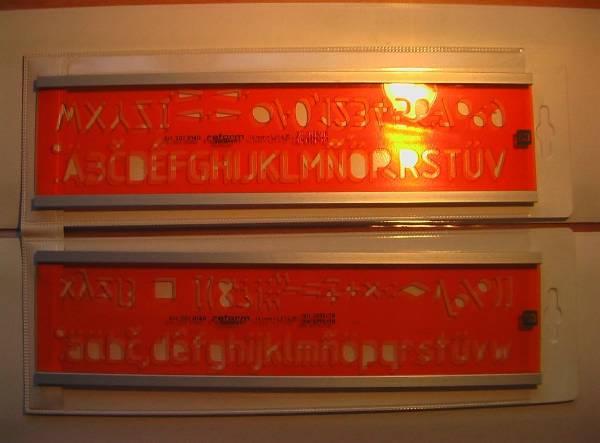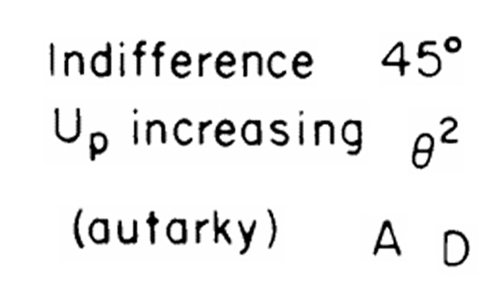
serifenlose Grafik-Schriftart aus einem wissenschaftlichem Paper der 70er Jahre gesucht
wie der Thementitel aussagt suche ich folgende Schriftart:
Das sieht aus wie eine der vielen typische (aus der Futura abgeleitete?) nordamerikanische Fibelschriften, also Schulbuchschriften. Diese Schriften sind nach dem zweiten Weltkrieg gelegentlich/selten auch in deutschen Lernmitteln aufgetauscht aber dann schnell wieder verschwunden. Einige Hochschuldruckereien haben in den guten alten Bleisatzzeiten bis in die 1980er solche Schriften noch verwendet. Ich habe da noch den einen oder anderen Schein rumliegen. Da gibt es einige freie Versionen, aber die sind alle etwas unpassend:
Deine Vorlage ist leicht condensed und ich finde gerade keine solche Schrift, habe diese aber schon mehrfach gesehen, nicht nur als Bleisatz. Leider ist mein Gedächnis nicht mehr das beste, das liegt aber daran, dass ich diese Schriften noch im Schul- und Studienbetrieb kennen gelernt habe.
PS: Die Frage wäre vielleicht in einem nordamerikanischen Forum besser aufgehoben?
Also ich hab hier was gefunden:
Das kommt dem was ich suche sehr nahe.
Ich komme aus der ehem. DDR und kenne diese Schriftarten auch von früher. Diese ganzen Schaubilder und sowas sahen ganz ähnlich aus.
der Tip mit der Schablonenschrift ist nicht schlecht. Mein Chef, (Professor für Physikalische Chemie) hat mir mehrfach erzählt, dass es bis in die 90er Jahre die Regel war, dass die Beschriftungen für wissenschaftliche Abbildungen in Papern oder auch Dissertationen/Habilitationen mit Schablonen, Rubbelbuchstaben oder Schreibmaschine erstellt wurden. DIN-Schablonenschrift war aber quasi der Standard, ein paar Schablonen finden sich bei uns im Institut immer noch in einigen Schubladen. Die Abbildungen selbst wurden mit Zeichentusche aus den Originaldaten reingezeichnet.
Schön, wenn die Schablonen benutzt haben. Ich hab bei meinem Freund auch schon ein paar alte sprachwissenschaftliche Veröffentlichungen gesehen, die mit Schreibmaschine getippt sind und dann z.B. griechische Wörter einfach mit der Hand in dafür gelassene Lücken gekrakelt worden :hammer:
So hat mein Vater seine Dissertation über Merkmale der russische Sprache geschrieben: den deutschen Teil auf der heimischen Optima mit mehreren Durchschlägen, den russischen Teil handschriftlich. (Ich weiß nicht mehr, ob mit dolle aufdrücken oder auf jeden Durchschlag separat.) In den 80ern. An einer Slawistikfakultät. Kyrillische Schablonen oder Schreibmaschinen gab’s da nicht, von Computern ganz zu schweigen. DDR-Alltag, eben.